「美文字になって
自分に自信をつけたい!」
だけど
書道教室に行く暇もないし
ペン字講座も高いしなあ...
でも
今のままだと
字が汚いからって
子供たちにバカにされるし
板書が苦手だから
授業にも自信が持てない...
だから
どうしても
美文字になって
子供や同僚に褒められて
自信をつけたいあなたへ!!
まずは僕のことを話します。
実は
僕は小学生の時に
習字教室に通っていて
字を書くのが得意でした。
「まあ字が上手くても
何も役に立たないけどね」
教育大学に入るまでの僕は
そう思っていました。
というか実際そうでした笑
字が上手いくらいじゃ
クラスの人気者になれないし
先生に褒められることも特にないし
親も見慣れてきてるし
字が上手くても
自分に自信が持てませんでした。
そもそも
字を人に見せる機会って
高校生までの間にあんまり無いですよね
友達にノート見せるとか
先生に当てられて黒板に書くとか
書道の授業とか
そんなもんなんなんですよね。
字が上手くても
そもそもあんまり認知されない...
もうちょい褒めて欲しいのにな...
これが
僕の高校生までの心境です。
ここからが
教育大学に入ってからの気持ち
1年生と2年生のときに
地元の中学校で
授業のサポートをする
という活動をしました
そのときに思いました
「この先生字下手だな...」
「でもこの人は上手いなあ」
「あの先生こんな字なんだ」
そして僕は気付きました
「先生って
めっちゃ人に字見られる!!」
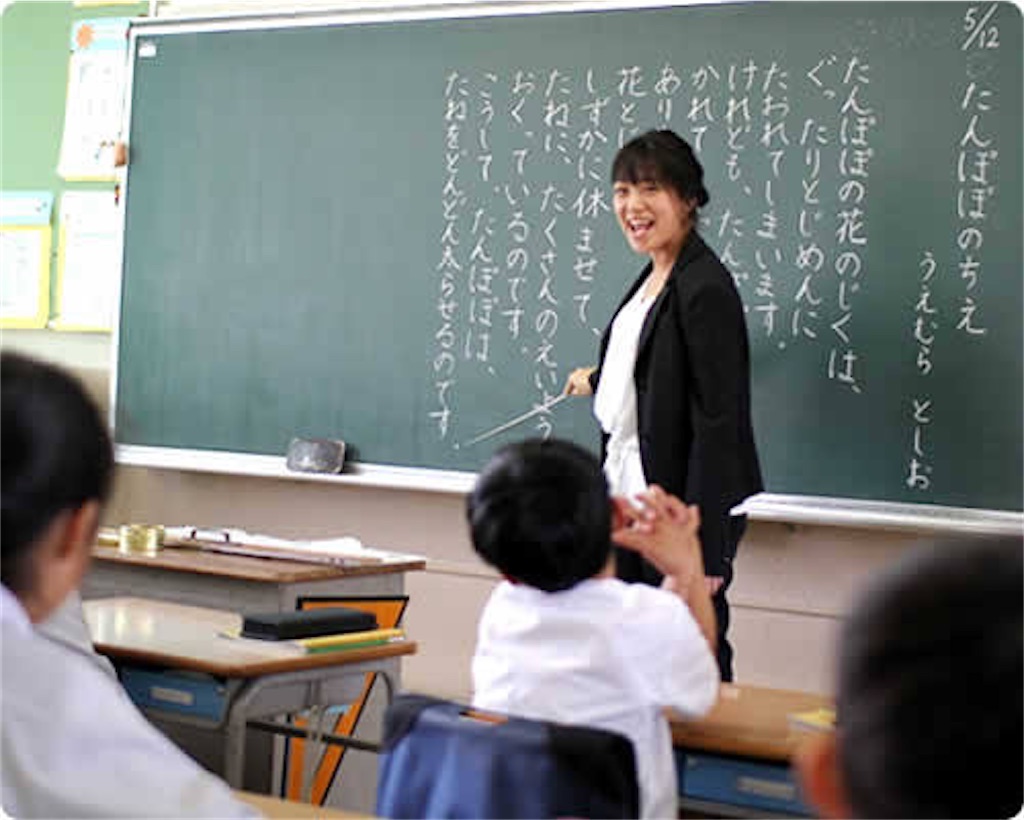
それに気づくと
現場の先生たちの字が
余計に気になってきました。
まず気になったのが
習字の時間です。
学校現場では
制度的に字の巧拙は問わずに
習字の授業ができます。
「それって怖いよなあ」
僕はそう思いました。
さっきのを逆に考えると
字が下手でも
習字の授業をさせられる
ということもあるということです。
実際現場を見てみると
先生が、教科書に書いてある
習字のポイントを
必死に説明していました。
字を書くのが
得意な先生ではなかったので
口頭で説明するしかないのです。
その先生は
習字の実力が伴っていないので
手本を見せられずにいました。
なので
説明はどこか自信が無いし
子供達を見ても
成長があまり見られませんでした。
実際にその先生は
「俺字上手くないから
書写の授業はそれっぽいこと
言うだけになっちゃうんだよね」
と言っていました。
その先生自身が
書写の授業に負い目を
感じていました。
また
特に気になったのは板書です。
大抵の授業で
先生が多くの字を板書します。
見る場面が多いし
みんなの前で書いてるし
1番目につきやすいですよね。
僕は国語専攻だったので
主に国語の授業を見学しました。
そこで感じたのが
字の綺麗さが
板書の綺麗さに直結している
ということでした。
もちろん
レイアウトの工夫も重要ですが
結局は字の集合なので
字の綺麗さが重要なんです。
そんな体験から
「先生なら
字の綺麗さを活かせる!!」
そう思いました。
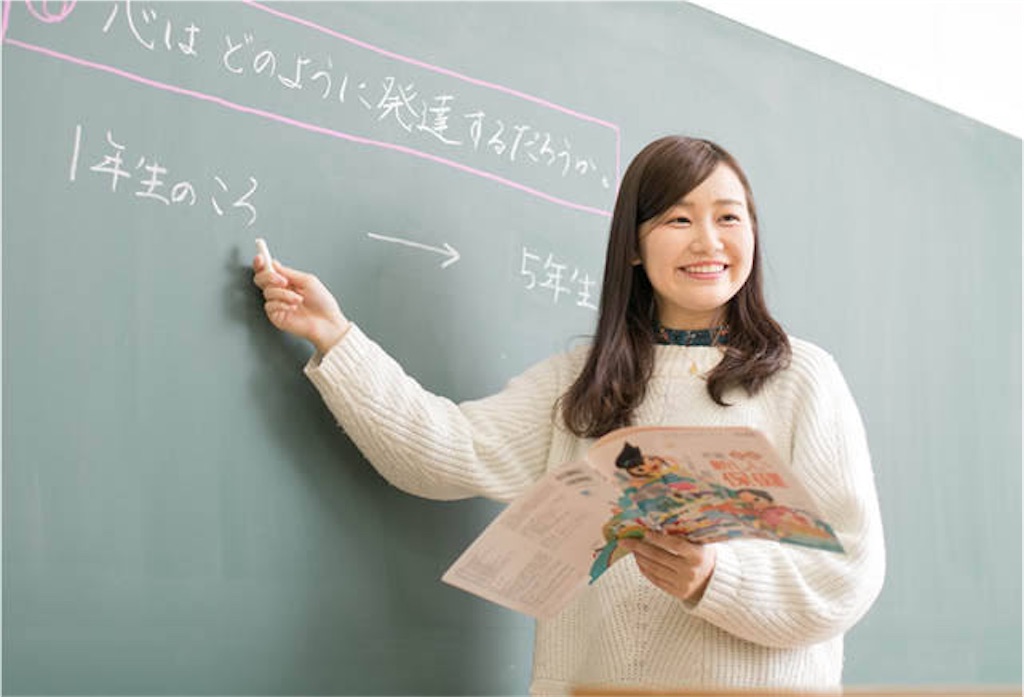
3年生と4年生では
教育実習をしました。
実際に授業するために
友達同士で模擬授業をしたり
板書の練習をしたりしました。
そこでみんな口を揃えて
「板書がやばい....」
と言っていました。
色んな実習生の板書を
見てきましたが
正直、めちゃめちゃ見づらいです
まっすぐ書けてないし
字の大きさがまばらだし
変なとこで改行するし
そもそも字が上手くないし...
とにかく
現場の先生との差が
如実に出ていました。
授業の内容以前の問題です。
板書の練習はしましたが
多くの実習生は
「板書が見づらかったよ」
と生徒にも言われていました。
実際の授業だと
すごく急いで板書するので
余計に板書が下手になるんです。
特に国語の授業は
他の授業と比べて
板書の文量が多いです。
その中で
板書に不安を抱えていると
その不安が授業に影響します。
「やばい上手く書けなかった」
「板書見づらくなっちゃった
どうしよう...」
なんて不安を抱えて
授業をしているので
自信なさげで信頼できない
授業になってしまいやすいです。
そうして実際に
授業で板書がうまく書けず
「字が上手だったらなあ...」
「書道を習っておけば...」
と言っている実習生もいました。
ここから
ちょっとだけ
僕の自慢になります(笑)
最初の方に言ったように
僕は書道を習っていたので
字を書くのが少し得意でした。
そして
大学に入学してから
ある書道の先生に
出会いました。
その人は
書道の協会の理事をするほど
書道を極めている人でした。
しかも
書道の本のお手本を書いたり
美術館で書道展として展示したり
するようなすごい人でした。
その人が教えてくれるのは
とても簡単で単純なことでした
教えてもらっていましたが
(そんな簡単なことで
今更変わらないでしょ...)
と思っていました。
そう思いつつも
とりあえず実践してみました。
すると
自分の字が
見違えるくらい
上手になりました
ほんのちょっとの工夫と
ほんのちょっとのコツで
一気に上達したんです。
なので
板書は初めから上手でした。
「なんでそんな上手く書けるの?」
って言われてました(照)
正直僕以外にも
上手な子はいましたが
みんな過去に書道を習っていて
字を書くのが得意でした。
周りにも褒められ
板書に少し自信があった僕は
実際の授業でも
見やすい板書がかけました。
見やすい板書が書けても
実習生で
授業は全然下手だったのですが
「板書がうまく書ける!」
という得意科目があったので
その点では自信を持って
授業をすることができました。
しかも
字が上手なのが先生に伝わり
習字の授業も任されました。
「君が習字出来て助かった!」
と担当教員の方にも
言っていただけて
非常に嬉しかったです。
さらに学級日誌の返事も
「やっぱ字が上手いと
先生っぽくていいね!」
と言っていただけました。
実習生としての
僕の強みは
字が上手いこと
たったひとつでした。
ですがそれだけで
いろいろなことを任されて
色んな人に褒められました。
なにより
字が上手いことが報われて
すごく嬉しかったし
すごく自信がつきました。
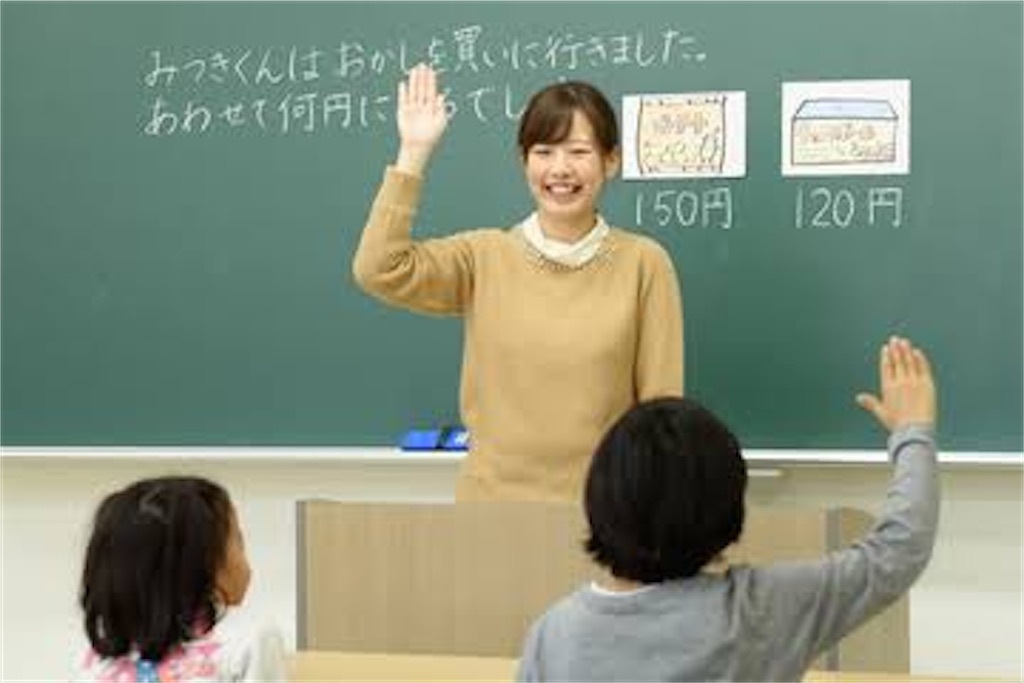
字を書くことに関して
自信が持てたので
大学の後輩に書道やペン字を
教えるようになりました。
すると
すぐに字が変わりました。
その後輩はもともと
めちゃめちゃ字が下手でした。
下の画像くらいのレベルですね。
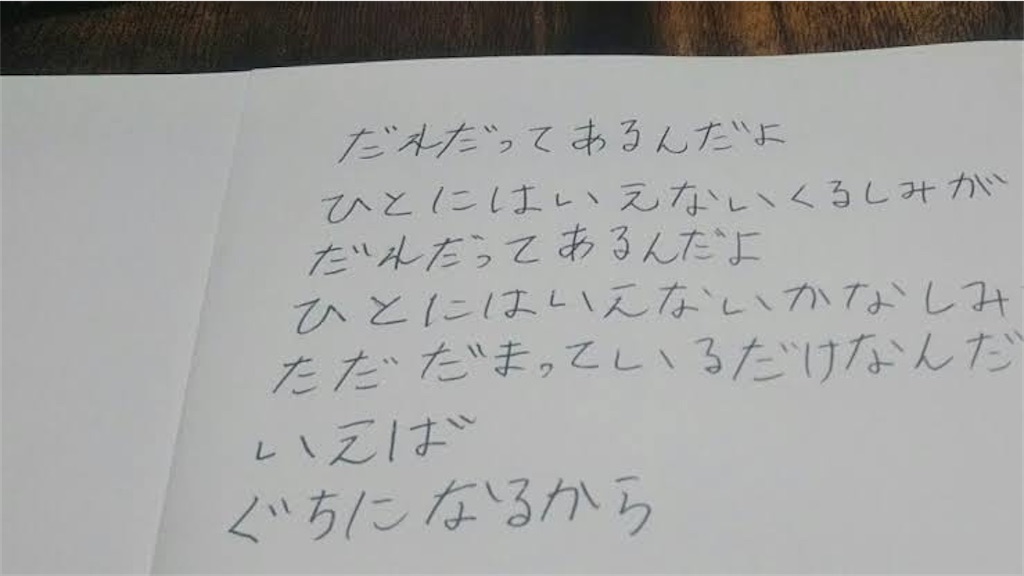
ノートを見られたくない...
大事な書類書くとき困る...
字を書きたくない...
字が苦手な後輩は
そんなふうなことを言ってました。
鉛筆の字が書けないと
書道の字も上手く書けません。
書写の時間には
上手く書けないこともあり
ふざけて書いてごまかしていました。
「どうせ上手に書けないから
仕方ないですよねー」
と言っていました。
しかし
字が上手くなってからは
その子の周りの見る目が
変わっていきました。
「教授にも褒められたし
友達にも褒められた!」
「なんで上手くなったか聞かれました!」
字を教えた後輩は
そんなふうに言ってました。
人前で字を見せる人が
字を書くのが上手くなると
めちゃくちゃ
周りに褒めてもらえる!
ということに気づきました。
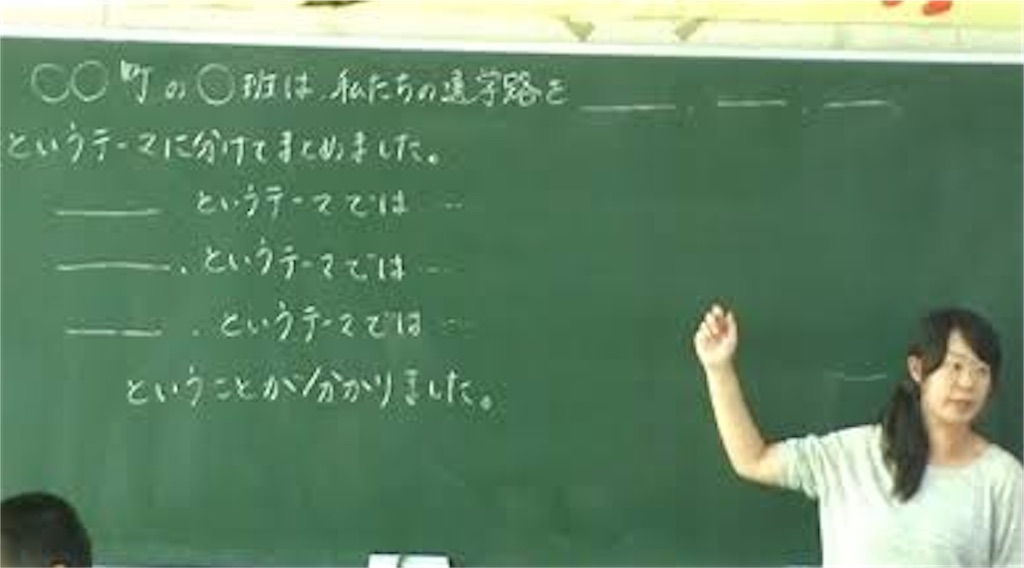
「そうなりたい人はもっと
たくさんいるのでは??」
特に先生や先生になりたい人は
そうやって自信をつけたいと
思ってるんじゃないか?
僕が字を教えた後輩たちは
教わり始めて
次に人に見せる頃には
周りに褒められ出しました。
今度は後輩だけじゃなくて
もっと必要としてる人の
手助けを出来るんじゃないか
そう思い、今回
今日から字が上手くなる方法
をPDFにまとめ
人に褒められたい
自分に自信をつけたい
方々に捧げることにしました
書道教室は敷居が高いし
ペン字講座は値段が高すぎ
だからって周りに頼るのも恥ずかしい
だからこそ
Webを使い第三者の私に
手助けできることがあると思います
このPDFは僕や僕の後輩と同じように
・字が上手くなって自分に自信をつけたい
・周りにとにかく褒められたい
・板書が得意になってもっと良い授業がしたい
漢字の上達に直結します
また
書道では
本来は「とめ」の部分を
ハネで書くことがあります
いわゆる行書の書き方ですが
これが出来ると
非常にこなれた字になります
ハネをマスターするだけで
多くの漢字が得意になったり
こなれた字を書けるように
なるんです
「じゃあ、どうしたら
ハネが上手になるの?」
何をしたらいいか分からない人は
二段階に曲げる
ことを意識しましょう!
上の画像を見てください!
ハネを作るために
一回折れをつくっています
このように
余分に折れることで
筆先が整い、綺麗なハネが
非常に簡単に作れます
さらに
ハネの直前に折れがあることで
よりハネが鋭くなり
洗練された字になります
ちなみに
このように二段階にしないと
ハネの直前が丸くなり
ボテっとした文字に見えます
コツを知るだけで
ハネは劇的に良くなるんです!
まずは今すぐに
自分の字を見返してみましょう!
すぐにできますよね?